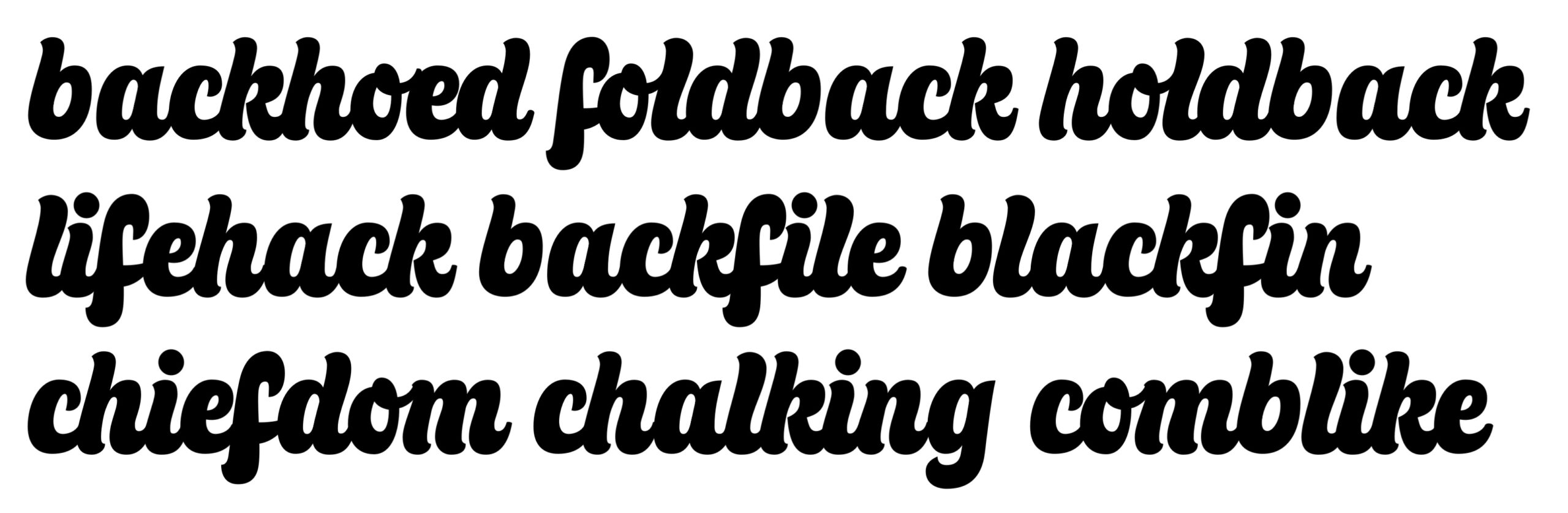
2026-09-19 – Насмотрелся на надписи Кирилла Ричерта и сделал шрифт по мотивам его букв. Может быть, буду использовать в своих леттерингах как основу.
2026-09-20 – Сделал строчные (латиницу и кириллицу). Начал прописные.
2026-09-21 – Сделал узкую версию. Может, так повеселее будет смотреться.
2026-09-23 – Сделал вчера эскиз прописных в новом шрифте, так показалось логичнее — так ищется форма, лучше, чем сразу в ФЛ делать буквы. А сегодня стал обводить их и на ходу доделывать.
29.09.2026 — Доделал все буквы, сделал довольно много (но пока недостаточно) альтернатив с росчерками и лигатур. Придумал название — Волна.